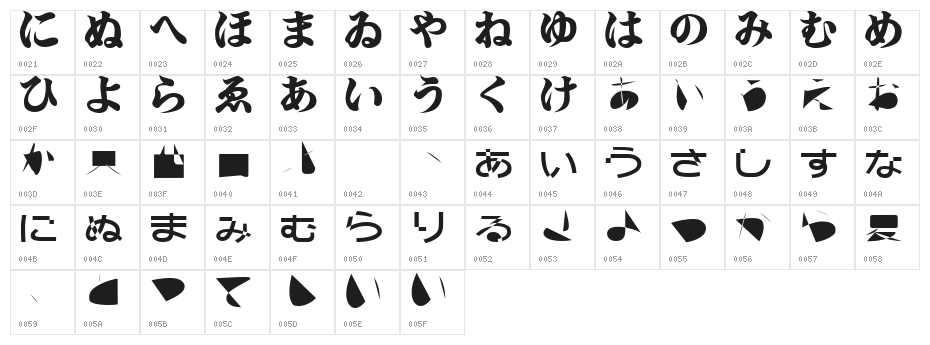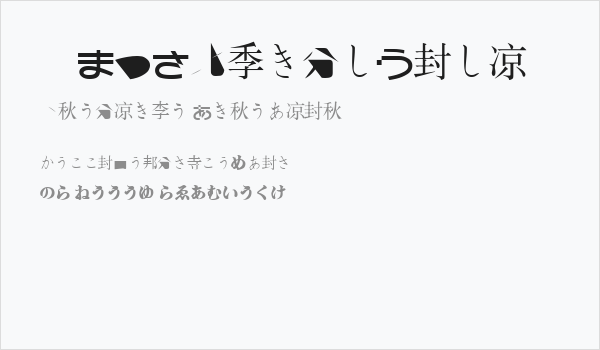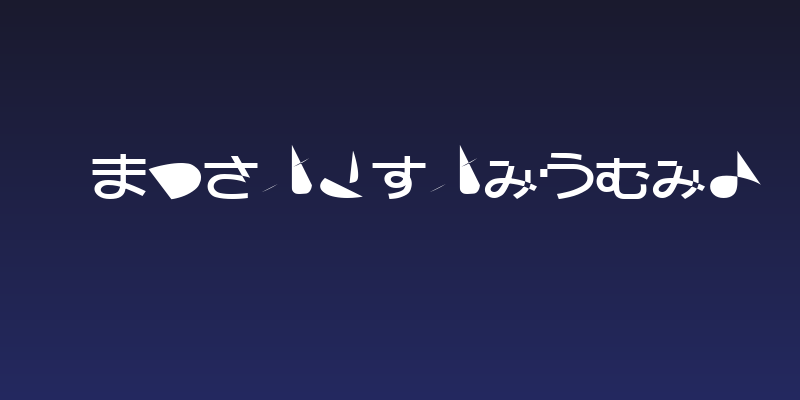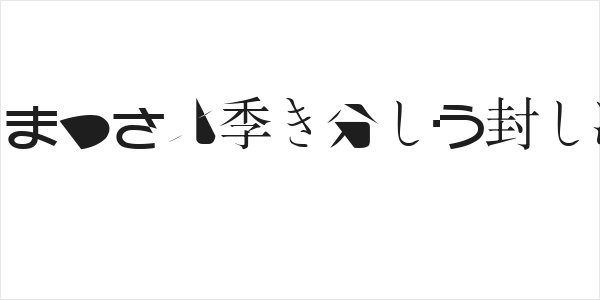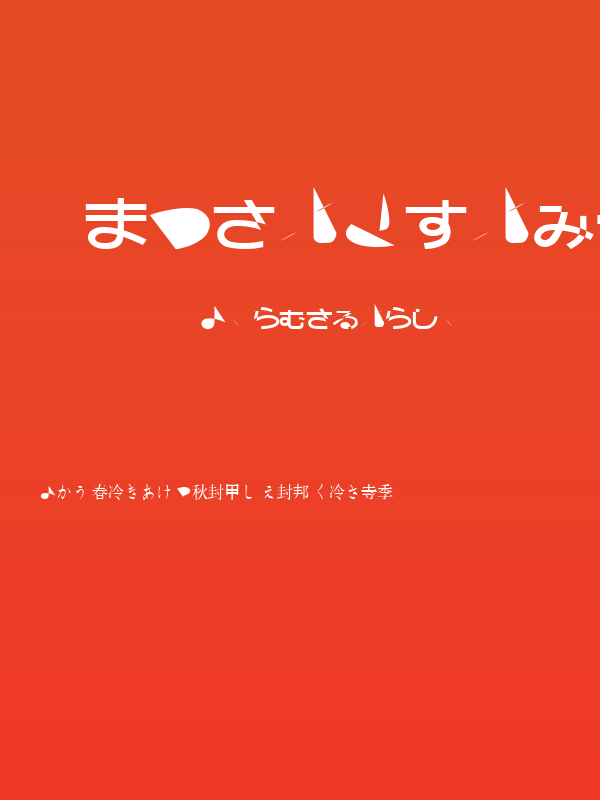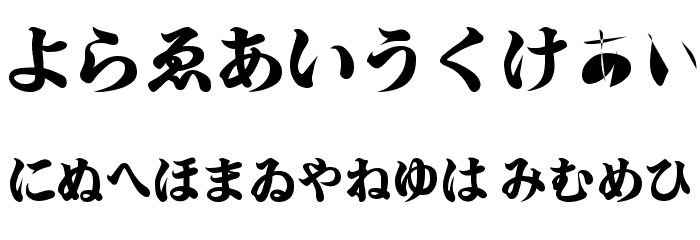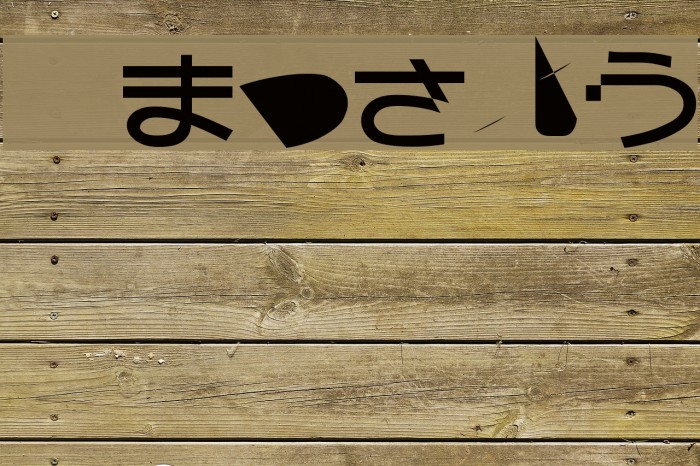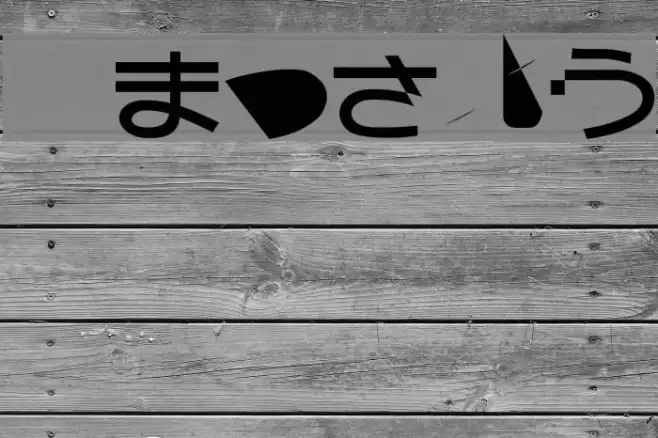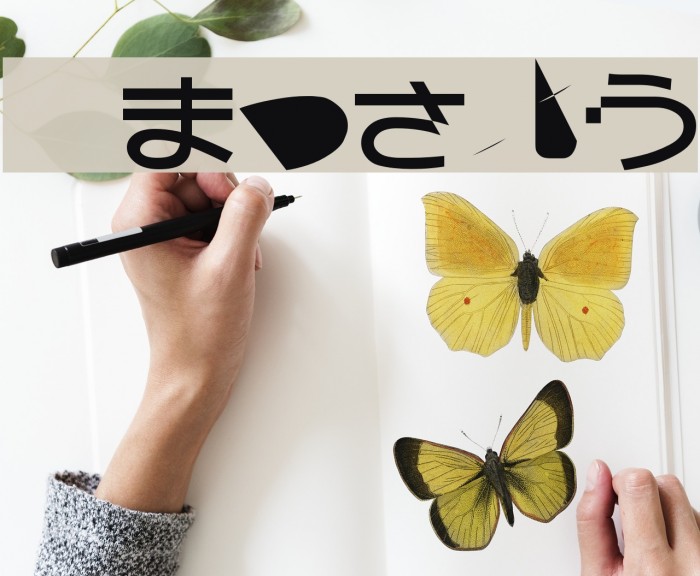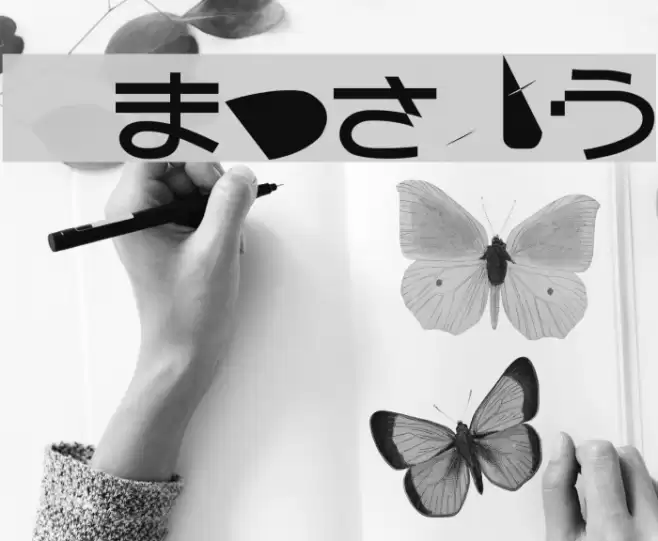
BMUGAsianFont Font
| Categorii | Asian |
| Stil general | Modern with traditional influences |
| Caz de utilizare | Headlines, Posters, Branding, Educational materials |
| Proiecte propuse | Japanese branding, editorial headlines, posters, cultural event materials, educational resources. |